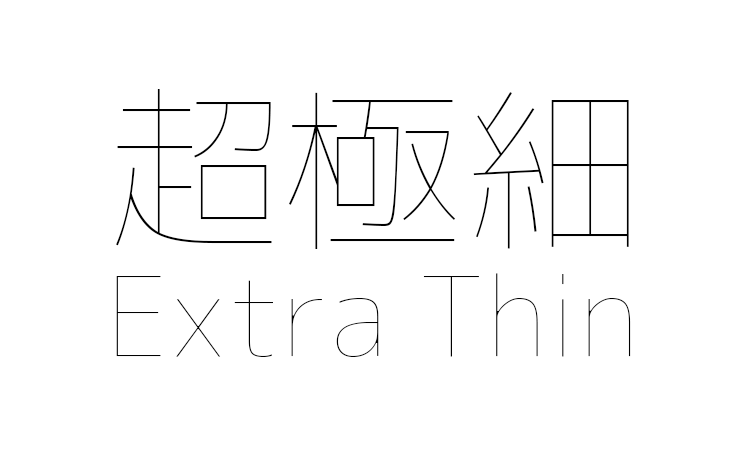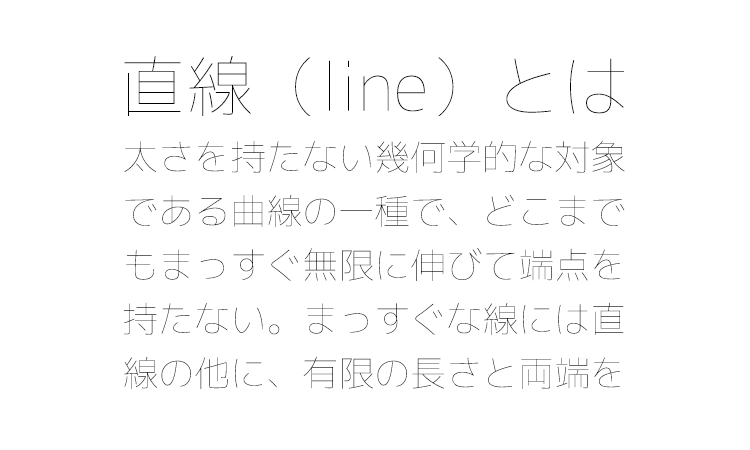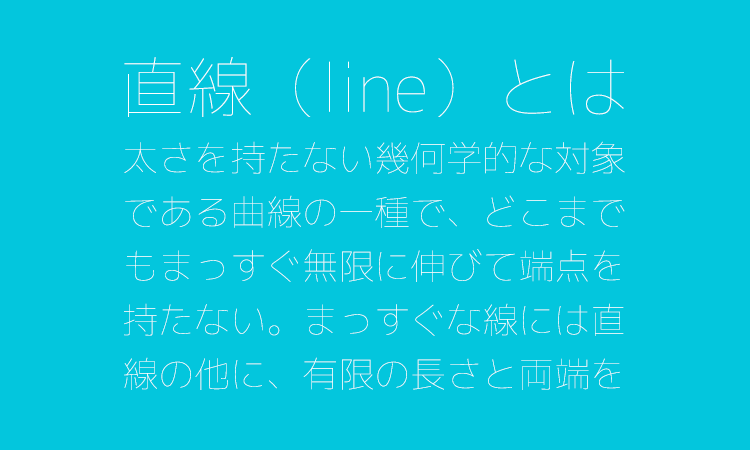
超極細ゴシック体
超極細ゴシック体は、Extra Lightよりもさらに細い、Extra Thinウェイトの超極細日本語フォントです。細いボールペンで、きっちりと真っ直ぐな線を引いたような、さっぱりとした仕上がりになっています。とても細いためかすれる可能性がある印刷には向いていません。デジタルコンテンツでの使用がおすすめです。
白背景での使用例
超極細ゴシック体のサンプル1
青背景での使用例
超極細ゴシック体のサンプル2